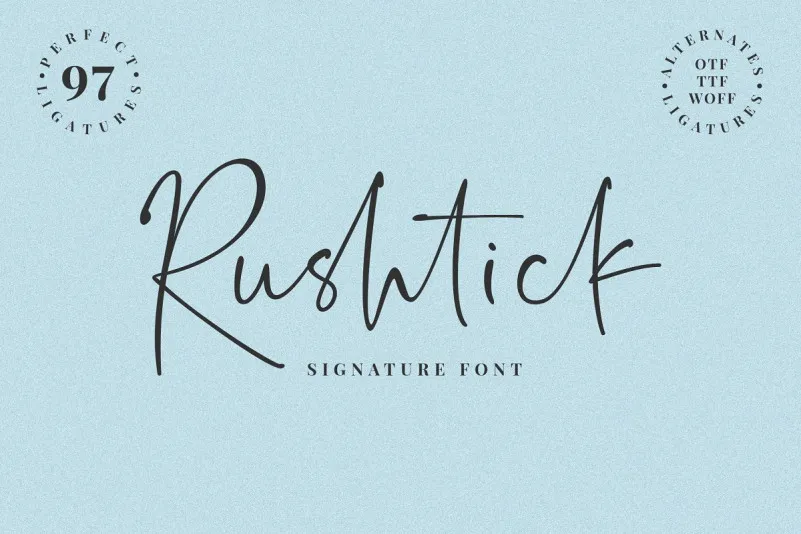
Desculpe pela confusão, mas não há informações suficientes na descrição original para fornecer uma descrição envolvente e natural específica para a página de download desta font. A descrição original foca principalmente no estilo moderno do tipo, suas possíveis aplicações como logo e assinatura, sem muitas características específicas ou detalhes que descrevam sua aparência única. Para uma descrição mais envolvente e natural da font ‘Rushtick Signature Font’, eu precisaria ter mais informações sobre o design específico desta fonte. A fonte promete um estilo elegante e moderno, perfeito para criações de assinatura sofisticada ou estilos gráficos contemporâneos. O tipo seria ideal para criar logos criativos, assinaturas elegantes ou adicionar um toque personalizado a postagens em blogs, cards ou outros materiais digitais.